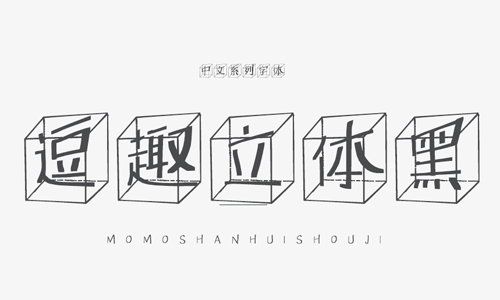
逗趣立體黑字體是一款涂鴉風(fēng)格的黑體字體,透視立體的視角結(jié)構(gòu)加上立方體的框架修飾,讓字體充滿了趣味和科技感,能夠應(yīng)用于文本裝潢、信息展示、網(wǎng)頁設(shè)計、篆刻制模、數(shù)據(jù)制作、裝潢設(shè)計、計算藝術(shù)設(shè)計、視覺設(shè)計、字帖等一切合法應(yīng)用場景,歡迎有需要的朋友前來下載使用。